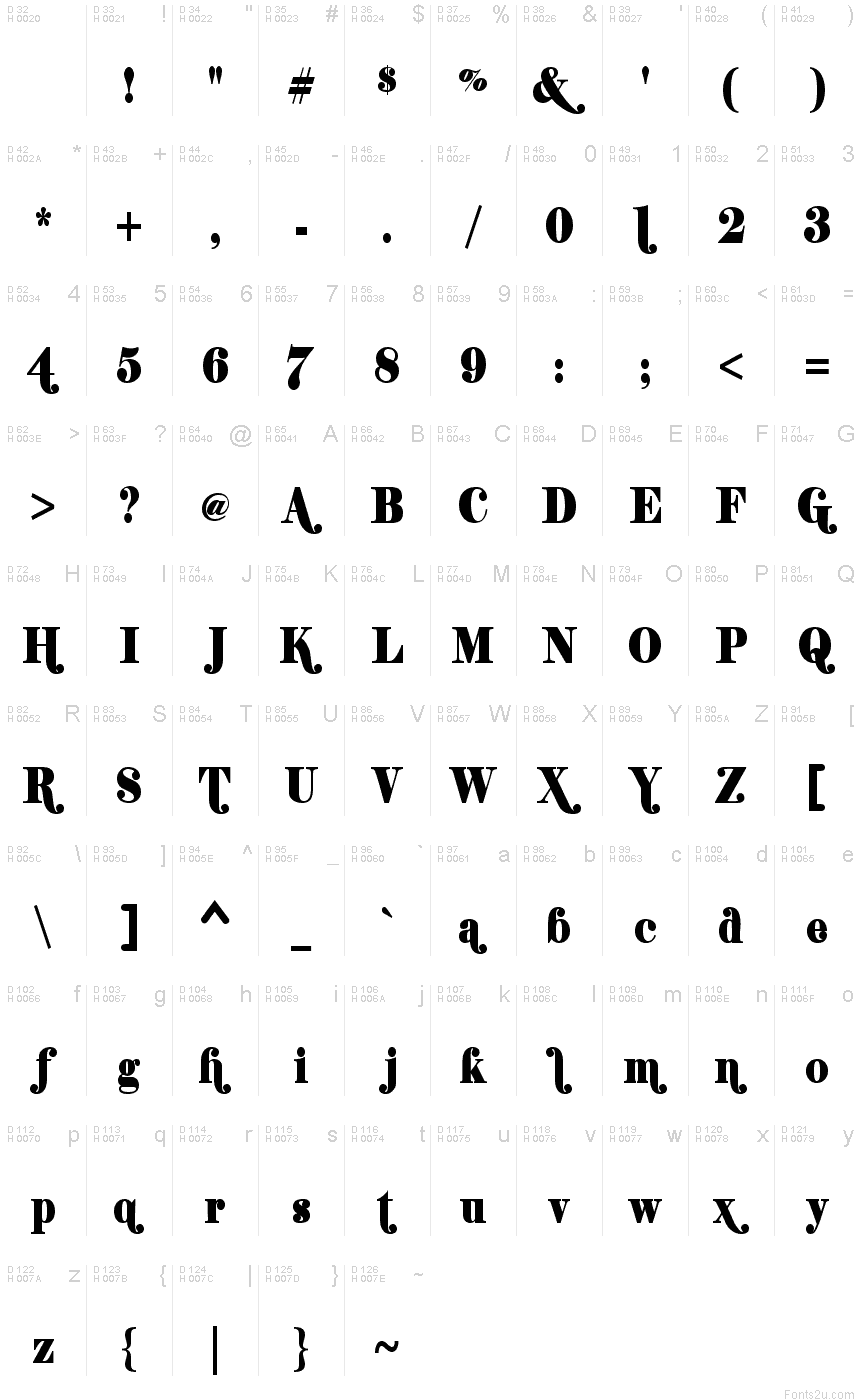
Shifty Chica autorstwa Raya Larabie to bezpłatny, retro krój typu display o zabawnym klimacie przełomu lat 60. i 70. Litery łączą w sobie proste, klasyczne proporcje z dużymi, zaokrąglonymi zawijasami i kropelkowymi zakończeniami, dzięki czemu całość prezentuje się elegancko, zadziornie i nieco teatralnie, ale bez zbędnego przepychu.
Świetnie sprawdzi się na plakatach, opakowaniach butikowych, w brandingu kawiarni, na okładkach płyt czy ulotkach eventowych, wszędzie tam, gdzie nagłówek potrzebuje nuty vintage. Jako darmowy font, doskonale nadaje się także do napisów, wizytówek i krótkich haseł typu logo, ponieważ pętelki nadają nawet krótkim słowom dekoracyjny, przyciągający wzrok rytm.
Shifty Chica